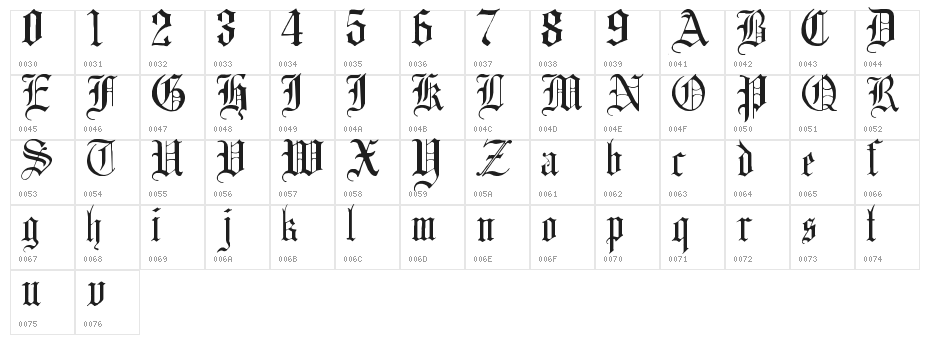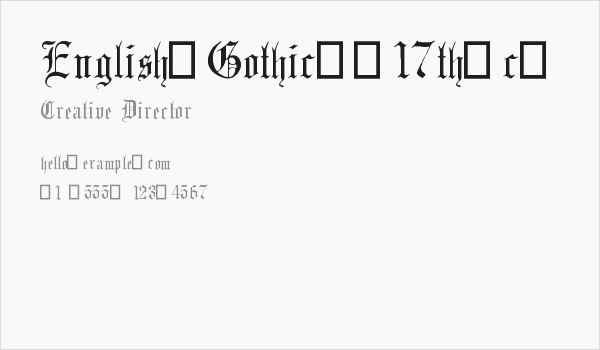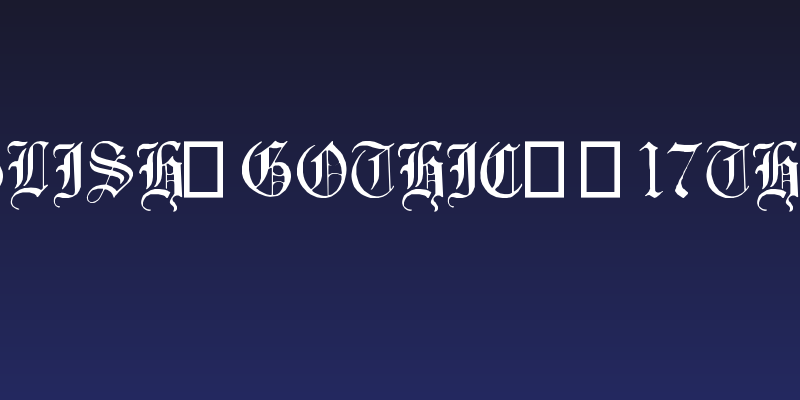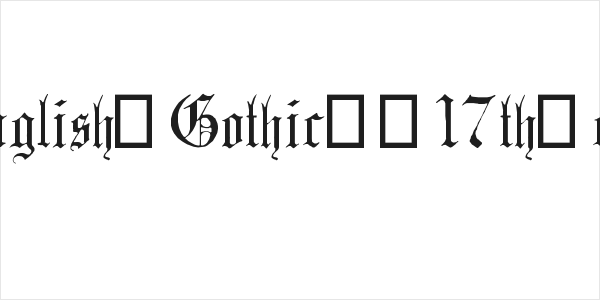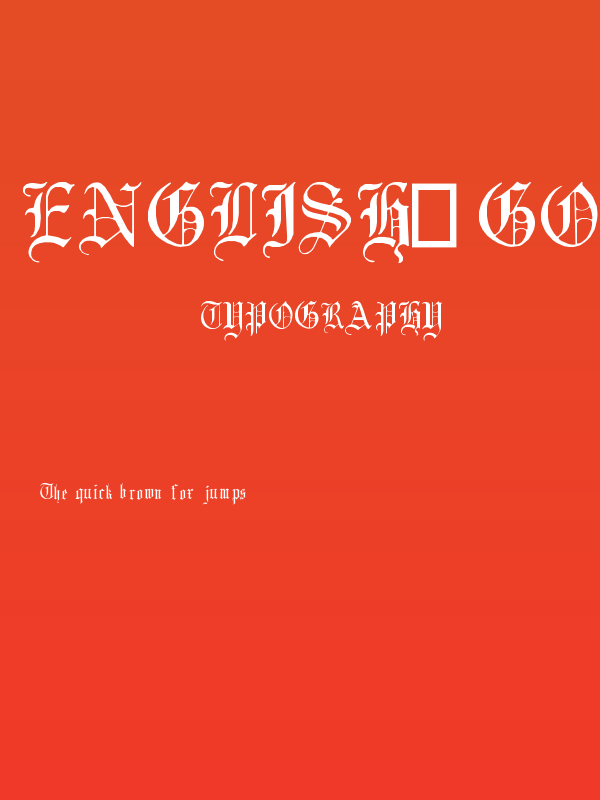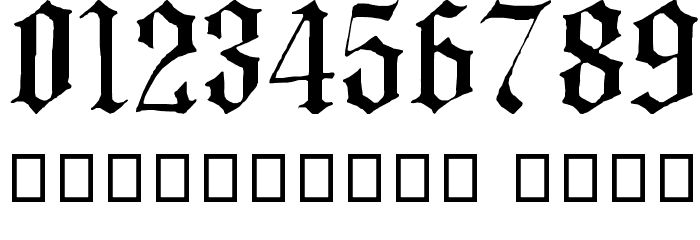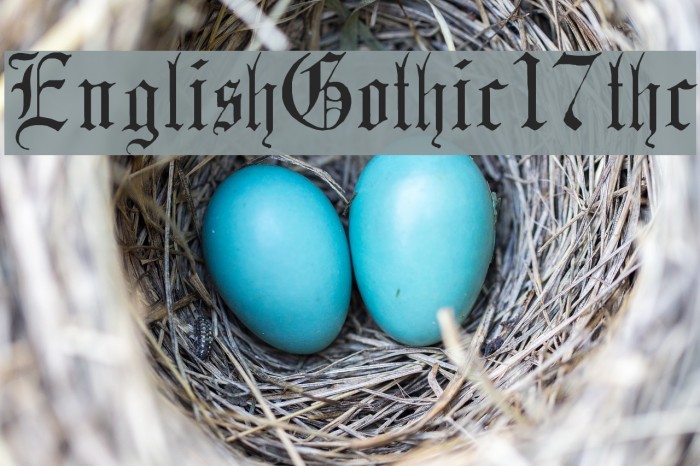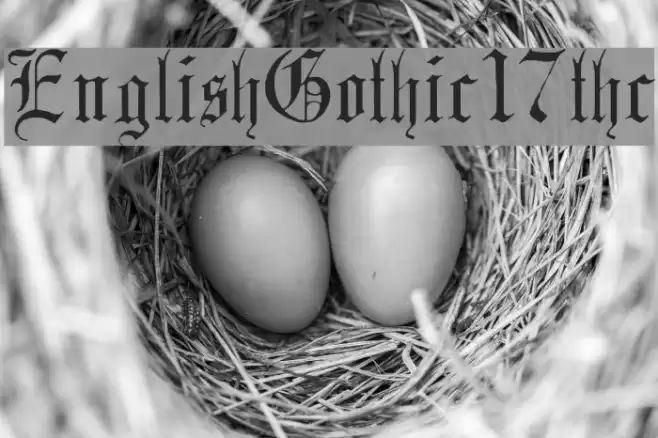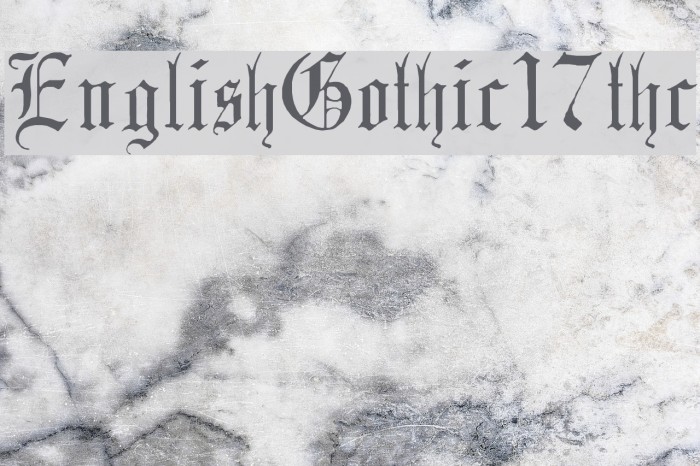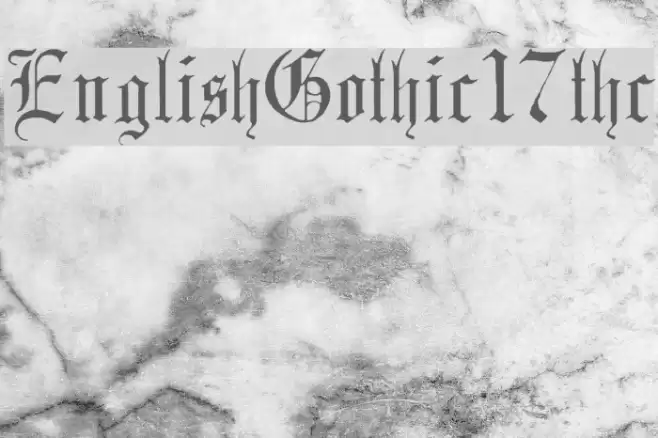
English-Gothic--17th-c- Font
| Estilo general | Vintage |
| Caso de uso | Logos, Headlines, Decorative purposes |
| Proyectos propuestos | Perfect for historical documents, formal invitations, certificates, or any project requiring a traditional and authoritative look. |